ฟอนต์พังแบรนด์จบ! วิธีเลือก Font ฉลากสินค้าให้อ่านง่าย ยอดขายพุ่ง
บนชั้นวางสินค้าที่เต็มไปด้วยคู่แข่ง การตัดสินใจซื้อของผู้บริโภคอาจเกิดขึ้นในเวลาเพียงไม่กี่วินาที ในสมรภูมินี้ “ฉลากสินค้า” คือด่านหน้าสำคัญที่ทำหน้าที่สื่อสารกับลูกค้าโดยตรง แต่หลายครั้งที่ผู้ประกอบการมุ่งเน้นไปที่การออกแบบกราฟิกจนละเลยองค์ประกอบพื้นฐานที่ทรงพลังที่สุด นั่นคือ “ฟอนต์” หรือรูปแบบตัวอักษร การเลือกฟอนต์ที่ไม่เหมาะสมอาจส่งผลกระทบต่อยอดขายและภาพลักษณ์ของแบรนด์ได้อย่างไม่น่าเชื่อ
หัวใจสำคัญของการออกแบบฉลากสินค้า
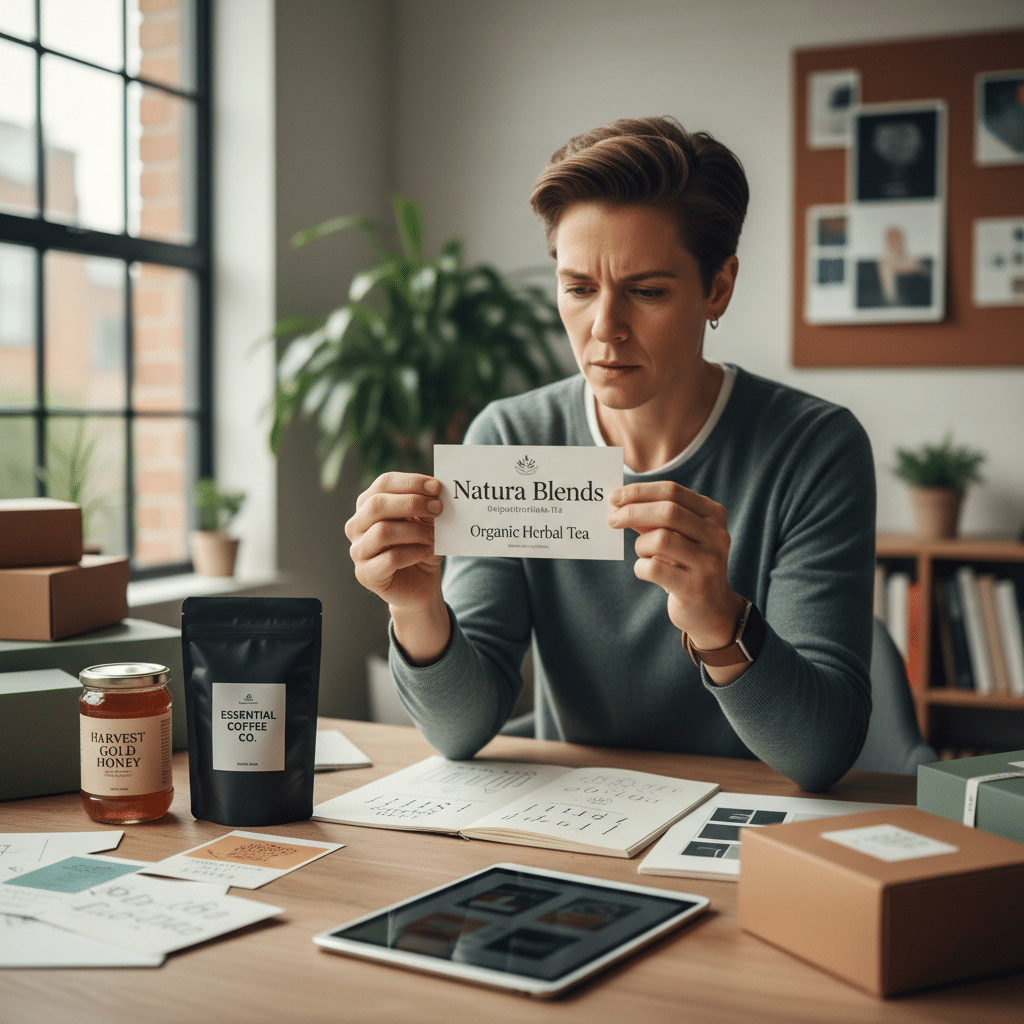
- ความอ่านง่ายเป็นอันดับแรก: ฟอนต์บนฉลากสินค้าต้องอ่านออกได้ง่ายและรวดเร็วภายใน 3 วินาที แม้จะมีขนาดเล็กหรือมองจากระยะไกล เพื่อให้ข้อมูลสำคัญเข้าถึงผู้บริโภคได้ทันที
- สะท้อนบุคลิกแบรนด์: รูปแบบของตัวอักษรสามารถสื่อถึงอารมณ์และความรู้สึกได้ ไม่ว่าจะเป็นความหรูหรา ความน่าเชื่อถือ ความเป็นมิตร หรือความสนุกสนาน การเลือกฟอนต์ให้ตรงกับตัวตนของแบรนด์จึงเป็นสิ่งสำคัญ
- สร้างความแตกต่างและน่าจดจำ: ฟอนต์ที่เป็นเอกลักษณ์และสอดคล้องกับผลิตภัณฑ์ จะช่วยให้สินค้าโดดเด่นบนชั้นวางและสร้างการจดจำในใจของผู้บริโภคได้ในระยะยาว
- หลีกเลี่ยงข้อผิดพลาดพื้นฐาน: การใช้ฟอนต์มากเกินไป หรือเลือกฟอนต์ที่สวยงามแต่ซับซ้อนจนอ่านยาก คือข้อผิดพลาดร้ายแรงที่สามารถทำลายความน่าเชื่อถือและภาพลักษณ์ของแบรนด์ได้
จิตวิทยาเบื้องหลังตัวอักษร: ทำไมฟอนต์ถึงสำคัญ
ปัญหา ฟอนต์พังแบรนด์จบ! วิธีเลือก Font ฉลากสินค้าให้อ่านง่าย ยอดขายพุ่ง ไม่ใช่เรื่องเกินจริง ในโลกของการตลาดที่การสื่อสารด้วยภาพมีความสำคัญสูงสุด ตัวอักษรหรือไทโปกราฟี (Typography) ถือเป็นองค์ประกอบทางภาพที่มีพลังในการโน้มน้าวและสร้างการรับรู้ได้ไม่แพ้รูปภาพหรือสีสัน ฟอนต์ไม่ได้เป็นเพียงแค่ตัวกลางในการถ่ายทอดข้อมูล แต่ยังเป็นเครื่องมือที่สามารถกระตุ้นอารมณ์ สร้างความไว้วางใจ และกำหนดทิศทางของภาพลักษณ์แบรนด์ได้อย่างลึกซึ้ง การทำความเข้าใจจิตวิทยาเบื้องหลังฟอนต์จึงเป็นกุญแจดอกแรกสู่การออกแบบฉลากสินค้าที่ประสบความสำเร็จ
สำหรับผู้ประกอบการ SME หรือนักการตลาด การเลือกฟอนต์ไม่ใช่แค่เรื่องของความสวยงาม แต่เป็นการตัดสินใจเชิงกลยุทธ์ที่ส่งผลโดยตรงต่อการรับรู้ของผู้บริโภค ฟอนต์ที่เหมาะสมสามารถทำให้ผลิตภัณฑ์ดูน่าเชื่อถือมากขึ้น ในขณะที่ฟอนต์ที่ผิดพลาดอาจทำให้สินค้าดูราคาถูกหรือไม่เป็นมืออาชีพได้ในทันที ดังนั้น การลงทุนเวลาเพื่อศึกษาและเลือกสรรฟอนต์ที่ใช่จึงเป็นการลงทุนที่คุ้มค่า เพื่อให้แน่ใจว่าข้อความที่ต้องการสื่อสารจะไปถึงกลุ่มเป้าหมายอย่างมีประสิทธิภาพสูงสุด
ความอ่านง่าย: กฎเหล็กข้อแรกที่ห้ามมองข้าม
ก่อนจะพิจารณาถึงความสวยงามหรือความคิดสร้างสรรค์ใดๆ สิ่งที่ต้องให้ความสำคัญเป็นอันดับหนึ่งในการออกแบบฉลากสินค้าคือ ความอ่านง่าย (Readability & Legibility) สองคำนี้แม้จะใกล้เคียงกันแต่มีความหมายแตกต่างกันเล็กน้อย
- Legibility หมายถึง ความชัดเจนของตัวอักษรแต่ละตัว ทำให้สามารถแยกแยะความแตกต่างระหว่างตัวอักษรได้ง่าย เช่น ‘ง’ กับ ‘ว’ หรือ ‘l’ กับ ‘i’ ฟอนต์ที่มี Legibility ต่ำมักจะเป็นฟอนต์ที่มีการตกแต่งประดับประดามากเกินไป หรือมีรูปทรงที่แปลกตาจนผิดเพี้ยน
- Readability หมายถึง ความง่ายในการอ่านข้อความทั้งประโยคหรือย่อหน้า ซึ่งเกี่ยวข้องกับการจัดวางตัวอักษร ขนาด ระยะห่างระหว่างตัวอักษร (Kerning) และระยะห่างระหว่างบรรทัด (Leading)
บนฉลากสินค้าซึ่งมีพื้นที่จำกัดและต้องแข่งขันกับสินค้าอื่นๆ อีกมากมาย ผู้บริโภคมีเวลาเพียงเสี้ยววินาทีในการกวาดสายตา หากพวกเขาไม่สามารถอ่านชื่อสินค้าหรือข้อมูลสำคัญได้ในทันที โอกาสที่สินค้าชิ้นนั้นจะถูกหยิบขึ้นมาพิจารณาก็จะลดลงอย่างมหาศาล ฟอนต์ที่ซับซ้อนหรืออ่านยากจึงเปรียบเสมือนกำแพงที่ขวางกั้นระหว่างผลิตภัณฑ์กับลูกค้า
การออกแบบฉลากสินค้าที่ดีต้องยึดหลัก “การอ่านง่ายใน 3 วินาที” เป็นเกณฑ์สำคัญ หากผู้บริโภคต้องใช้เวลามากกว่านั้นในการทำความเข้าใจว่าสินค้านี้คืออะไร นั่นหมายถึงการออกแบบที่ล้มเหลว
การสื่อสารบุคลิกของแบรนด์ผ่านฟอนต์
ฟอนต์แต่ละรูปแบบมี “บุคลิก” และสามารถสื่อสาร “น้ำเสียง” (Tone of Voice) ที่แตกต่างกันออกไป ลองจินตนาการถึงผลิตภัณฑ์บำรุงผิวระดับพรีเมียมที่ใช้ฟอนต์ลายมือแบบเด็กๆ หรือของเล่นเด็กที่ใช้ฟอนต์แบบตัวพิมพ์ดีดที่เป็นทางการ ความรู้สึกขัดแย้งที่เกิดขึ้นนี้สามารถทำลายความน่าเชื่อถือของแบรนด์ได้ทันที
การเลือกฟอนต์จึงต้องเริ่มต้นจากการกำหนดบุคลิกของแบรนด์ (Brand Personality) ให้ชัดเจนเสียก่อน แบรนด์ของคุณต้องการสื่อสารภาพลักษณ์แบบใด:
- หรูหราและคลาสสิก: มักใช้ฟอนต์ประเภท Serif ที่มีเส้นสายอ่อนช้อยและเป็นทางการ
- ทันสมัยและเรียบง่าย: นิยมใช้ฟอนต์ประเภท Sans-serif ที่มีความสะอาดตา ตรงไปตรงมา
- แข็งแกร่งและมั่นคง: ฟอนต์ประเภท Slab Serif ที่มีฐานหนาและดูหนักแน่นมักเป็นตัวเลือกที่ดี
- สนุกสนานและเป็นมิตร: ฟอนต์ที่มีลักษณะโค้งมน หรือฟอนต์ลายมือที่ไม่ซับซ้อนจนเกินไป สามารถสร้างความรู้สึกเข้าถึงง่าย
การเลือกฟอนต์ที่สอดคล้องกับบุคลิกของแบรนด์จะช่วยเสริมสร้างภาพลักษณ์ที่เป็นเอกภาพ ทำให้ผู้บริโภคสามารถเชื่อมโยงและจดจำแบรนด์ได้ง่ายขึ้น
เจาะลึกประเภทฟอนต์ และอารมณ์ที่ซ่อนอยู่
เพื่อการตัดสินใจเลือกฟอนต์ได้อย่างแม่นยำ การทำความเข้าใจลักษณะและอารมณ์ของฟอนต์ประเภทหลักๆ เป็นสิ่งจำเป็น โดยเฉพาะฟอนต์ไทยที่มีความซับซ้อนและต้องคำนึงถึงบริบททางวัฒนธรรมควบคู่ไปด้วย
| ประเภทฟอนต์ | ลักษณะและอารมณ์ | ตัวอย่างการใช้งาน / ฟอนต์แนะนำ |